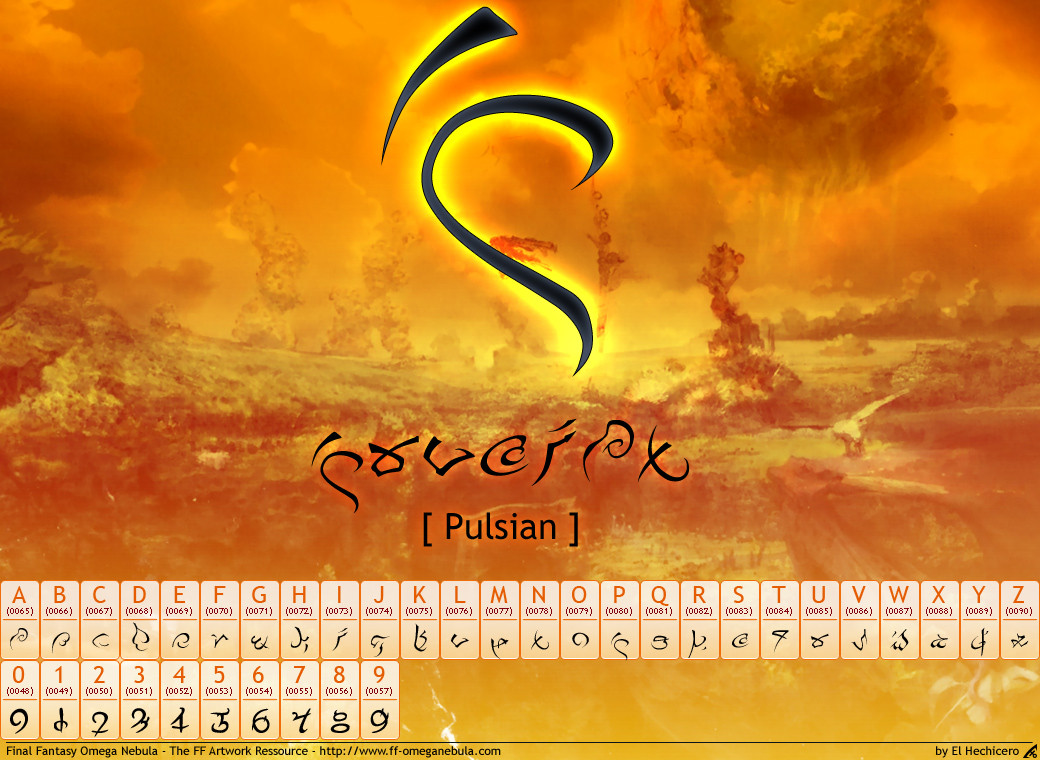
Police d'Γ©criture utilisΓ©e dans Final Fantasy 13---------
Font used in Final Fantasy 13
thought you should know the H and G lower case are the same.